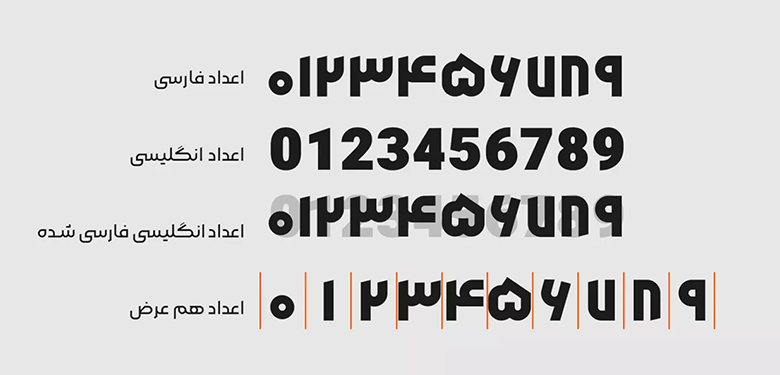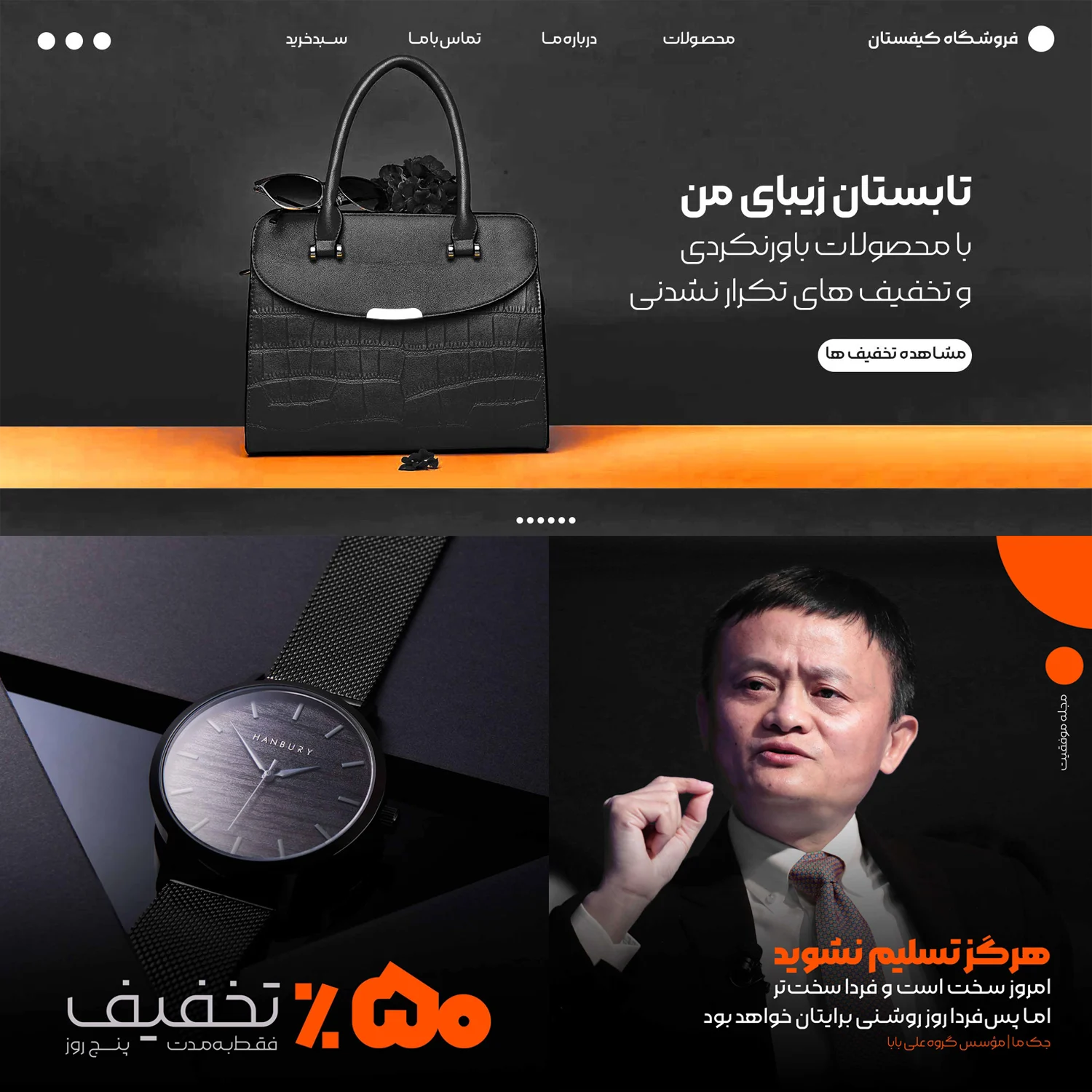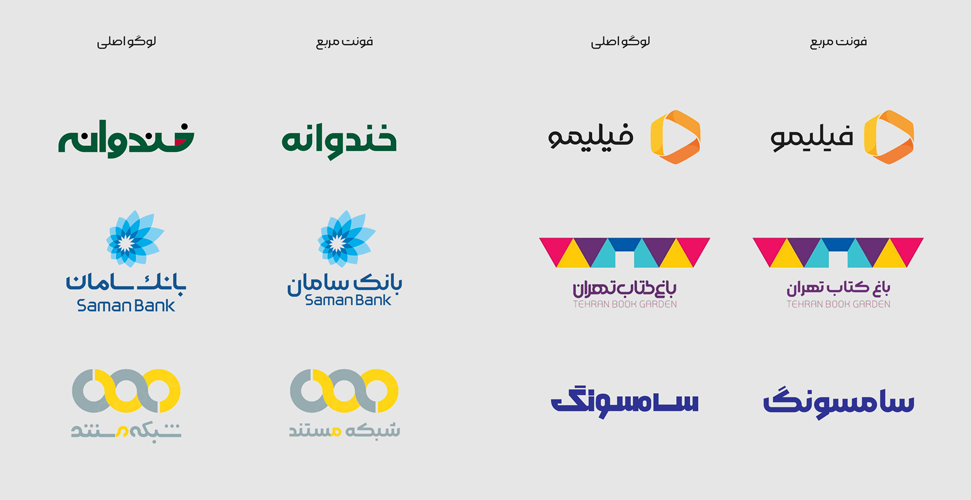
فونت مربع (Morabba)
حسن منظوری فونت مربع (به انگلیسی: Morabba) را که ریشه در خط کوفی بنایی دارد طراحی کرده و توسعه این فونت در ۹ وزن مختلف که از UltraLight آغاز شده و تا نسخه Heavy به انضمام فونت متغیر مربع وجود دارد، توسط شهرزاد اکبری صورت گرفته است. مربع یک فونت هندسی و مناسب برای عناوین و تبلیغات است.
خط کوفی بنایی سالها است که در خط و رسم فارسی مورد استفاده قرار میگیرد. عموما بیشتر این نوع طراحی را در لوگو تایپ مشاهده میکنیم که از جمله آنها میتوان به لوگوی بانک سامان یا شبکه مستند اشاره کرد که از این خط الهام گرفته شده است؛ اما با اینحال همیشه جای خالی یک فونت کوفی بنایی فارسی حس میشد که با تولد فونت مربع این خلا پر شد.
در ادامه این نوشته از سایت فونتچی به نقد و بررسی فونت مربع حرفهای خواهیم پرداخت؛ فونتی که ضمن دارا بودن طراحی مدرن با توجه به منحنیها و شکستگیهای خود، همچنان اصالت قدیمی خود را حفظ کرده و انتخابی عالی برای استفاده در متون کوتاه و عناوین است.
معرفی و بررسی فونت مربع (Morabba)
اگر بنا باشد یک دستهبندی عمومی و کلی برای فونت مربع درنظر بگیریم، میتوان آن را جزو فونتهای هندسی که با تلفیقی از منحنیها و شکستگیهای معتدل که باعث خلق فونتی با پهنای ثابت گردیده دستهبندی کرد.
بسیاری از کسب و کارها توانایی پرداخت هزینه یک لوگوتایپ اختصاصی را ندارند. استفاده از فونت هندسی مربع به عنوان ورد مارک، انتخاب هوشمندانه و به صرفهای برای اینگونه نیازها است که بتوانید یک لوگوتایپ اختصاصی بر مبنای ورد مارک طراحی کنید.
این میزان پهنا و در کنار آن داشتن ۹ وزن متنوع، مربع را به صورت کلی به فونتی با کنتراست بسیار بالا تبدیل کرده است که مناسب عناوین و تبلیغات است. در نتیجه میتوان از این فونت در انواع طراحی همچون بنر و پست شبکههای اجتماعی، بیلبوردهای تبلیغاتی، طراحی لوگو تایپ، طراحی وردمارک و حتی در سایت به عنوان فونت عناوین و تیتر که مناسب متنهای کوتاه هستند مورد استفاده قرار داد.
وزن و فونت متغیر مربع
فونت مربع فارسی در ۹ وزن متنوع طراحی شده است که وزن سنگین در نسخههای دیگر این فونت به آن افزوده شده است. وزنهای فعلی این فونت شامل خیلی نازک UltraLight تا سنگین Heavy است که در تمامی وزنها سعی شده تا جای ممکن فاصله بین حروف، کاراکترها و نقطهگذاری در فاصلهای کاملا مناسب و اعتدال در جای خود بنشیند.
فونت مربا متغیر نیز امکان استفاده از همه وزنهای قلم را در قالب یک فایل فونت فراهم میکند. کاربردیترین ویژگی این قلم برای تبلیغات و کارهای گرافیکی است که میتوانید با دانلود فونت مربع برای اینشات، کپ کات و فتوشاپ آثاری خلاقانه ایجاد کنید.
مزایا و ویژگی فونت Morabba
اگر بخواهیم به بررسی مزایا و قابلیتهای فونت مربع بپردازیم، میتوان به موارد زیر اشاره نمود:
پشتیبانی از زبانهای متنوع
با دانلود فونت مربع فارسی علاوه بر این زبان، امکان استفاده در زبانهای انگلیسی و عربی را خواهید داشت. زبان عربی با توجه به یکسان بودن حروف همان طراحی را دارد و همچنین از اعراب نیز پشتیبانی میکند که در ساختار کلی نسخه عربی و فارسی فونت یکسان هستند و صرفا تغییرات جزئی در برخی کاراکترها مانند حروف «ک، ی، ه، ؤ، ئ» دارند.
همچنین از نسخه ۲.۰ فونت مربع قابلیت پشتیبانی از زبانهای اردو، کوردی و لک نیز به این زبان افزوده شده است که شامل تمامی گلیفهای استاندارد این زبانها است.
اما در مقابل فونت مربع انگلیسی با توجه به نزدیکی این فونت به فونت Roboto، بر اساس همین فونت طراحی شده است که صرفا وزن و تغییراتی بسیار جزئی در آن ایجاد شده است و خبری از طراحی اختصاصی برای زبانهای لاتین در این فونت وجود ندارد.
پشتیبانی از ترکیبات و حروف جایگزین
ویژگی دیگر فونت Morabba پشتیبانی از حروف جایگزین و ترکیبات دو حروفی است که معمولا در هر نوع فونت معمولی یا دستنویس با شکلهای خاصی نوشته میشوند.
بهعنوان مثال کاراکترهایی نظیر «ر، ی، ک، گ، ه، الف» در این فونت از امکان جایگزینی حروف برخوردار هستند که میتوان در ابتدا یا انتهای کلمات به شکلهای مختلفی از آنها استفاده نمود.
فونت وریبل مربع با متغیر وزن و کشیده
فونت متغیر مربع نیز در این بسته گنجانده شده است که از دو متغیر برای تغییر وزنهای ۹ گانه و همچنین تغییر کشیدگی حروف بهره میبرد.
بر خلاف سایر فونتهای رایج، علاوه بر پشتیبانی از فونت متغیر بر اساس وزن، از قابلیت متغیر کردن فونت بر اساس فاصله یا همان کشیدگی حروف نیز پشتیبانی میکند. در تصویر بالا نسخه متغیر این فونت را در حالت تغییر وزن و در تصویر پایین بر اساس فاصله مشاهده میکنید.
وزن فونت در نسخه متغیر را میتوان به میزان ۲۵۰ تا ۹۰۰ تنظیم کرد و کشیدگی فونت نیز این امکان را میدهد که بدون نیاز به استفاده از چیدمان Justify برای همتراز کردن خطوط یا استفاده از کاراکترهای خط ثابت در حروف، کشیدگی را به دلخواه بر حسب هر حرف برای کلمات گوناگون به مقدار دلخواهی تنظیم کرد.
پشتیبانی اعداد فارسی و انگلیسی در فونت مربع
اعداد در فونت هندسی مربع رایگان برای همه زبانها از قابلیت مونواسپیس «اعداد همعرض» پشتیبانی میکنند. برای زبان فارسی و عربی که اعداد «۴، ۵ و ۶» ظاهری متفاوت دارد نیز گلیف اختصاصی طراحی شده که بر اساس زبان صفحه کلید اعداد تایپ میشوند.
این فونت جدای از اعداد همعرض برای همه زبانها از تزار عمودی نیز برخوردار است که کمک میکند در نرمافزارهای گرافیکی بهراحتی بتوانید تراز درست را روی اعداد تنظیم کنید.